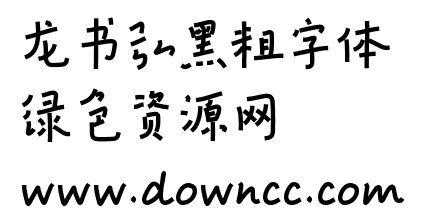
龍書弘黑粗體
龍書弘黑粗字體是在龍書弘黑體的基礎(chǔ)上加粗修飾而來,文字造型更加雄偉大氣,容易給人留下深刻印象,讓大家對標題文字的處理更加便捷,綠色資源網(wǎng)獨家推薦!
龍書弘黑粗體特色
龍書弘黑粗字體造型上十分q萌,有著童真童趣的憨厚可愛的藝術(shù)特色,字跡深顯隨意清爽的亮點,能給人眼前一亮的視覺效果。